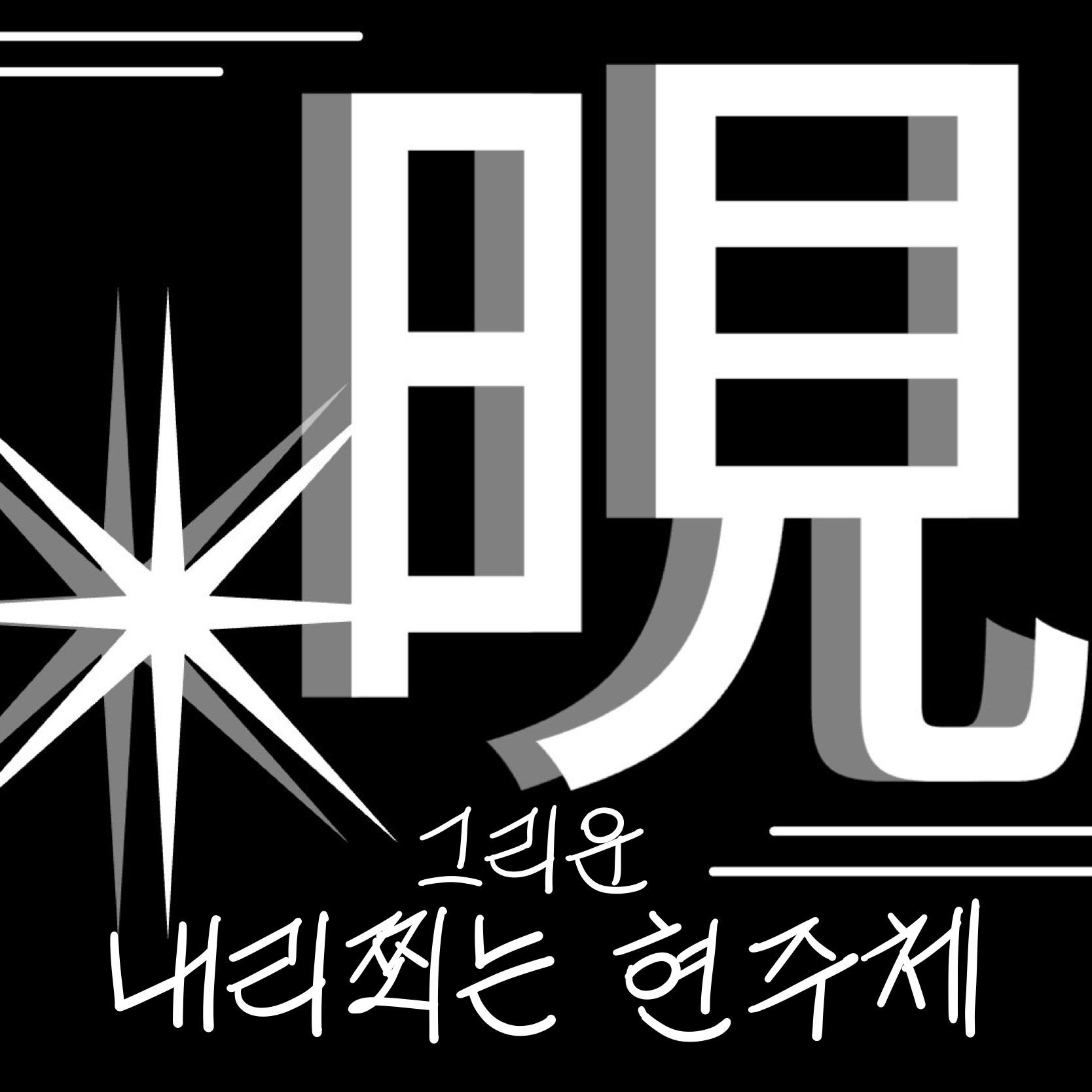
그리운 내리쬐는 현주체
Griun Naerijjoen HyunJu
그리운 내리쬐는 현주체 소개
그리운 내리쬐는 현주체는 꾸밈없이 써 내려간 손글씨의 분위기를 담은 폰트입니다. 부드럽게 이어지는 획과 자연스러운 글자 모양이 특징이며, 편안하면서도 감성적인 무드를 전해줍니다. 마치 일상 속 메모나 편지에서 볼 수 있도록 친근하고 따뜻한 인상을 담았습니다. 이 폰트는 글씨 본연의 자유로운 리듬을 살리는 데 집중하여 제작 되었습니다. 반듯하게 정리된 느낌보다는 손으로 직접 쓴 듯한 생동감과 온기를 담아, 보는 사람에게 더 진솔하게 다가갈 수 있도록 표현했습니다. 짧은 문구부터 긴 문장까지 부담 없이 사용할 수 있어, SNS 콘텐츠, 다이어리, 카드뉴스, 굿즈, 편지글 등 다양한 작업물에 잘 어울립니다. 소소한 일상과 진심 어린 마음을 담아내기에 좋은 폰트입니다. 당신만의 감정을 자연스럽고 따뜻하게 남겨 보세요.